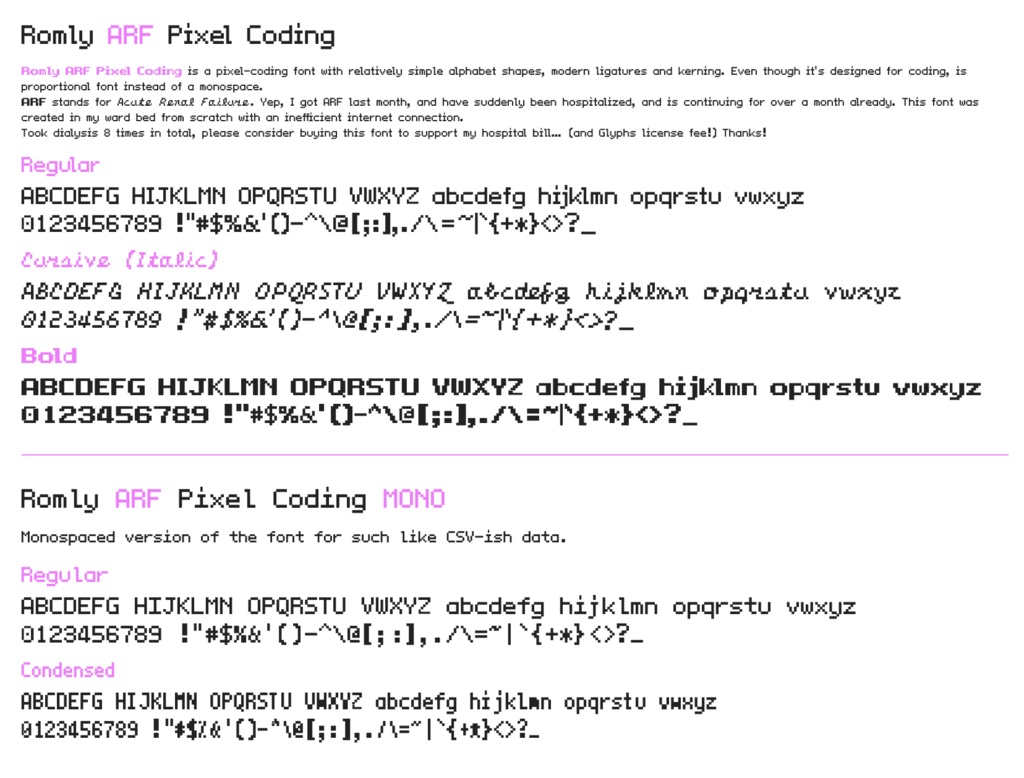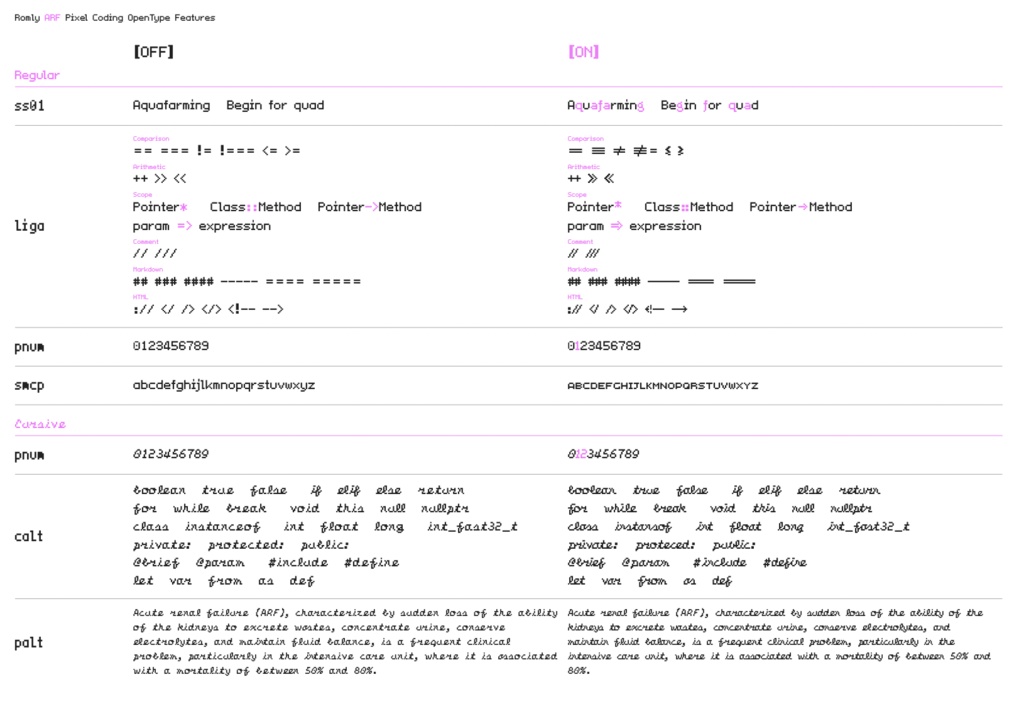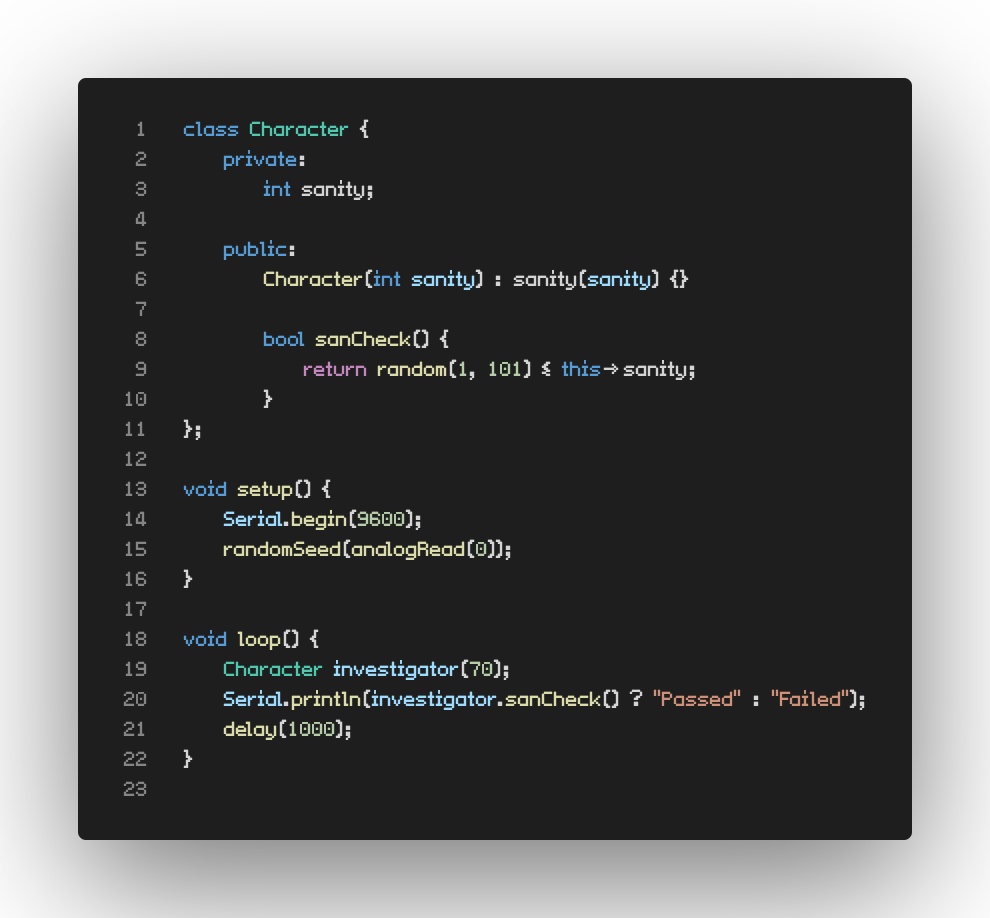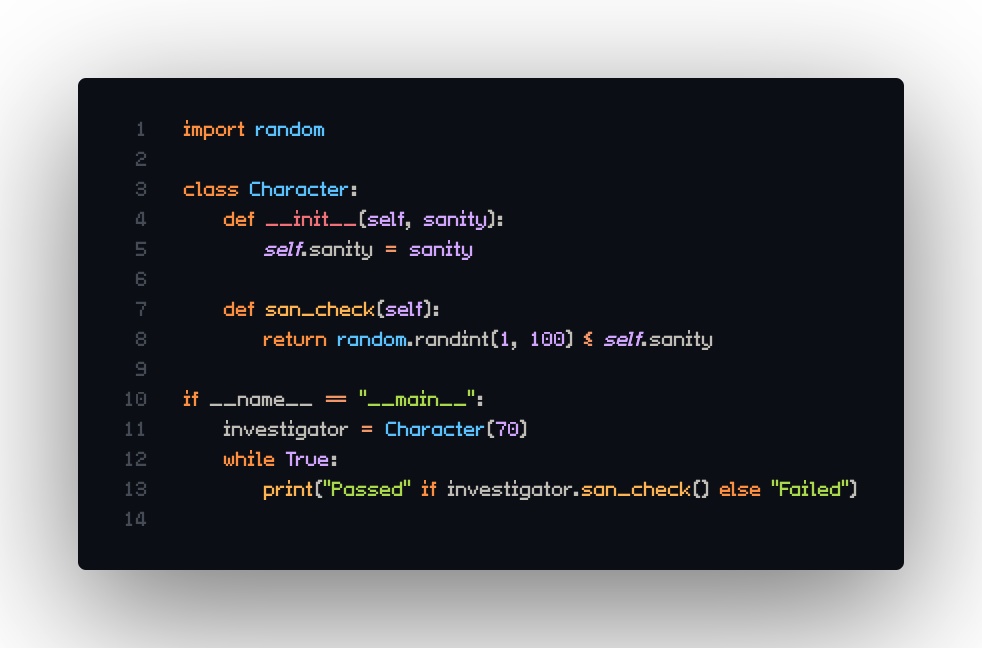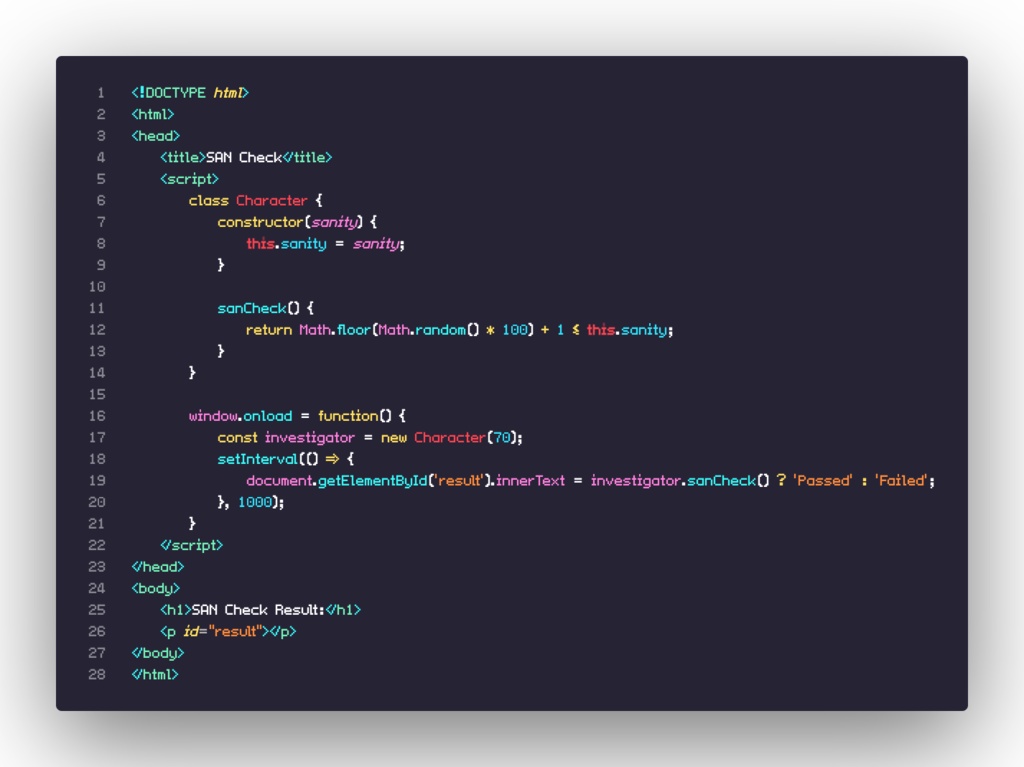
Romly ARF Pixel Coding フォント
Romly ARF Pixel Codingは、プロポーショナル幅のピクセルフォントです。コーディング用にデザインされていて、いくつかのモダンなリガチャを含みます。 アルファベットは比較的シンプルな5x7ピクセル、2ピクセルのディセンダで読みやすく、そこに今風のカーニングが施されていたり、プログラミングでよくあるリガチャが組み合わさっています。 今日日、美しいコーディング用フォントは山程ありますが、たまにはレトロスタイルなピクセルフォントもいかがでしょう。 斜体の小文字は筆記体風で、ピクセルフォントなのでちょっと読みづらいですがそこはご愛敬、お仕事よりもサンデープログラミング向けのフォントですから。使いづらい場合はカーシブ・ファミリーだけ削除しちゃって下さい。 CSVなどのデータ用には、Romly ARF Pixel Coding MONOも含まれています。こちらはすべて等幅のモノスペースフォントで、画面の専有スペースを抑えるコンデンスファミリーも付属しています。
制作裏話(ARFって何?)
実は先月突然『急性腎不全(ARF)』と相成って緊急入院、そのままかれこれ一ヶ月近く病院に缶詰です。それまでコツコツ作業していたフォースカーブ測定マシン #軸の秤 どころではなくなってしまいましたが、その代わり病床で完成させたのがこのフォントです。それこそフォント作成ソフトのお勉強から完成まで完全院内製を実現いたしました!笑 と言う訳なので、ARFと名付けたのでした。 有料ですが、売上は入院治療費(考えたくもない)に充てたいので、ぜひご購入ご検討を! フォント作成ソフト Glyphs のライセンス料も払わなきゃいけなくなっちゃったので……